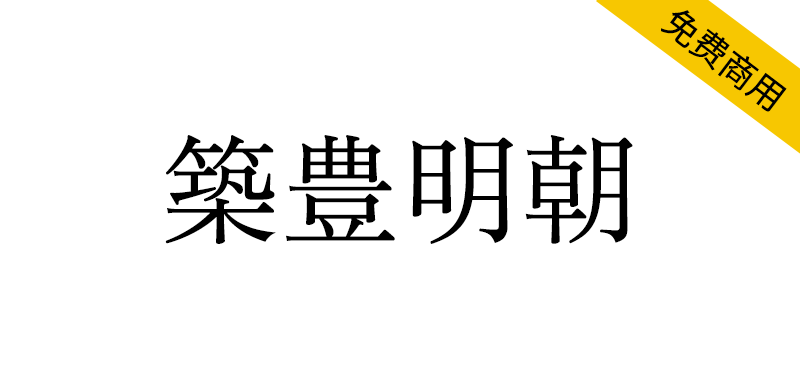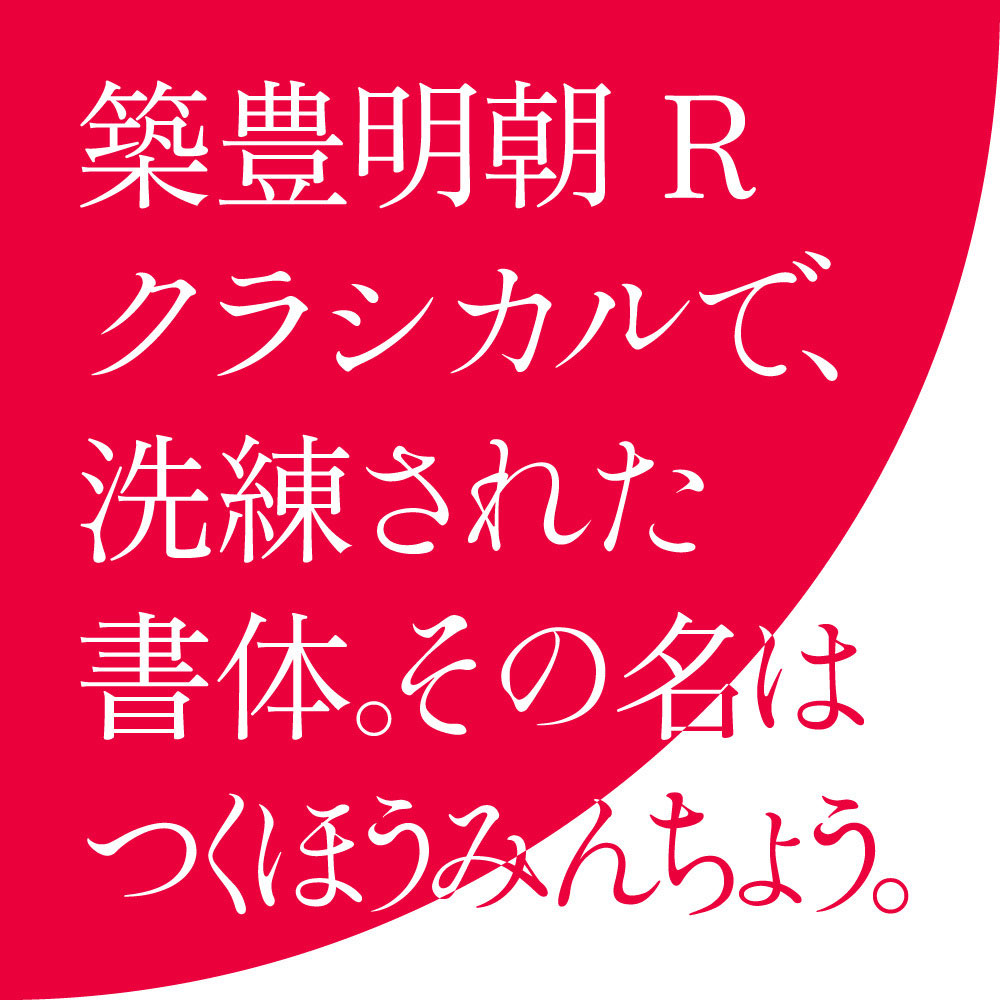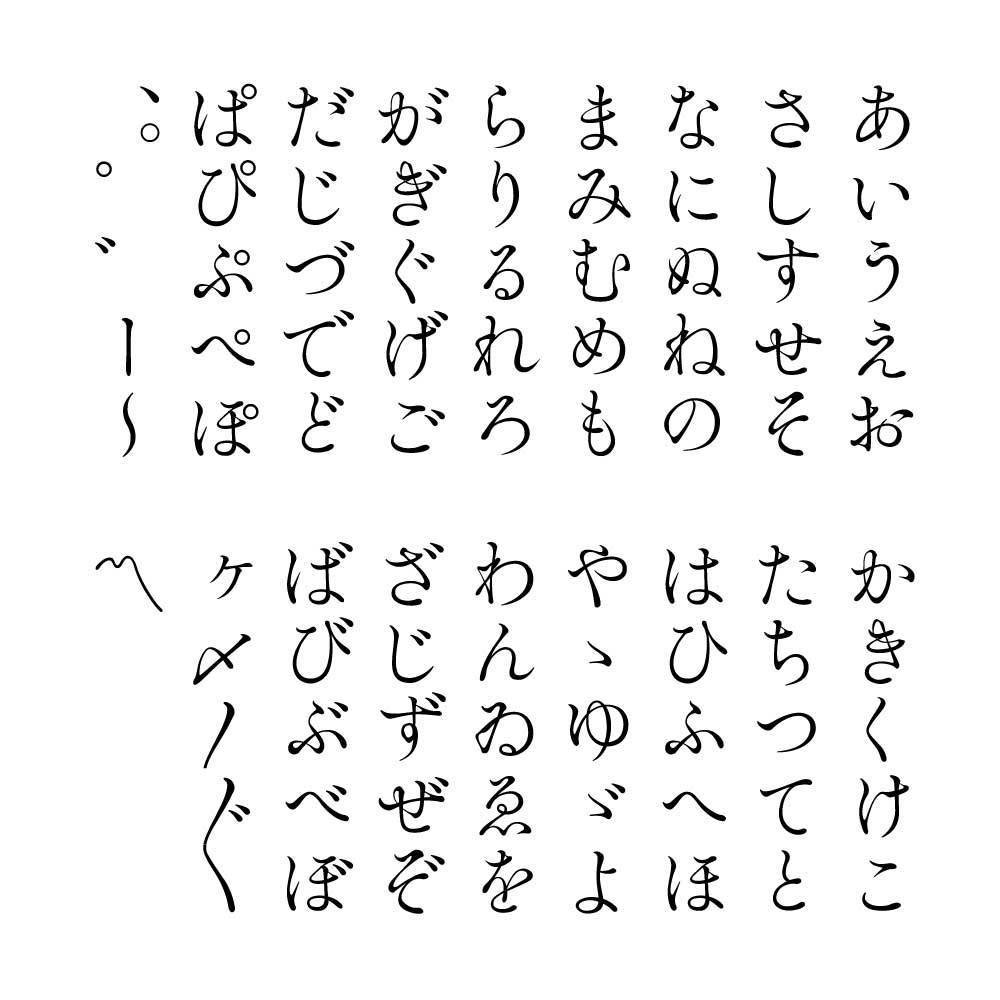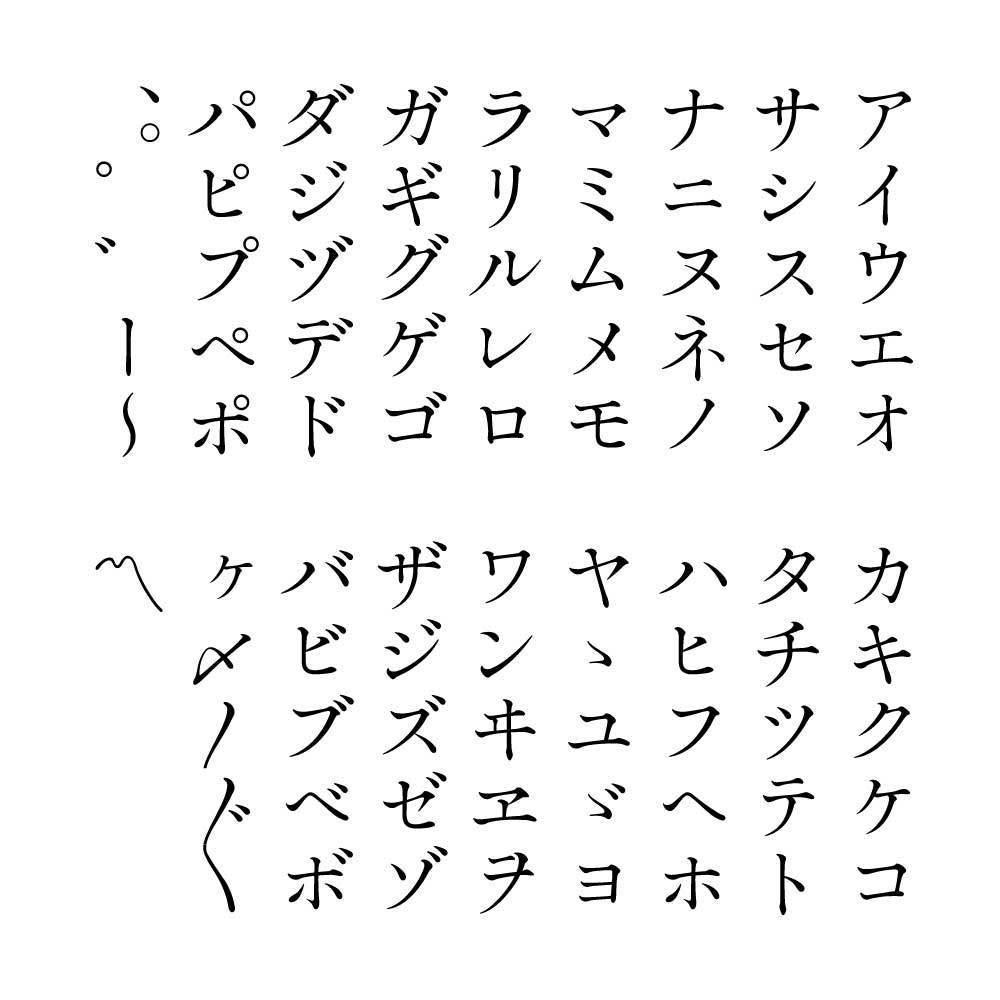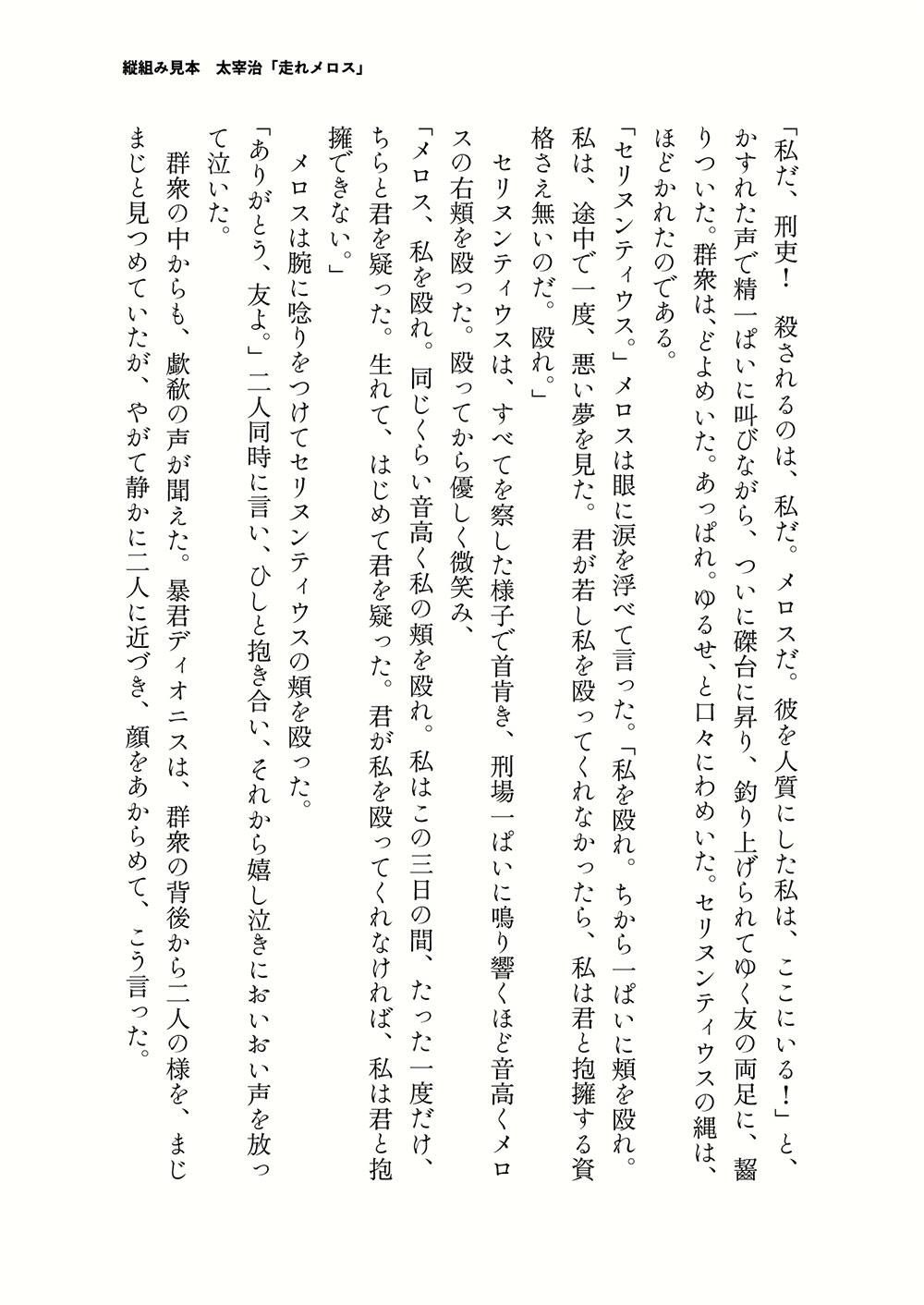
揭秘筑丰明朝:一款颠覆传统认知的日系字体!它巧妙融合筑地五号系的经典韵味与现代设计美学,通过调整笔势走向,让毛笔的灵动感与柔和特质得到极致展现。正文、标题皆宜,更以SIL开源授权免费商用,为你的创意项目注入独特东方韵味。
筑丰明朝(築豊明朝)这是一款以筑地五号系传统正文字体为灵感设计的明朝体字体。在保留传统韵味的同时,通过调整部分假名的笔势走向,进一步强化了毛笔的灵动感与柔和特质。其独特的字形设计不仅适用于正文,用于标题或标语时亦能引人注目。汉字与西文部分采用「ZENオールド明朝 Regular」字体。
築豊明朝(つくほうみんちょう)は築地五号系の伝統的な本文向け明朝体を意識して作られたかな書体です。伝統な部分を残しつつ、一部のかなの脈絡を変更することで筆の動きや柔らかさをより強調させました。独特な字形もあり、本文だけではなく、見出しやタイトルでも使っても目を惹きつけられるかもしれません。漢字や欧文は「ZENオールド明朝 Regular」からお借りしています。